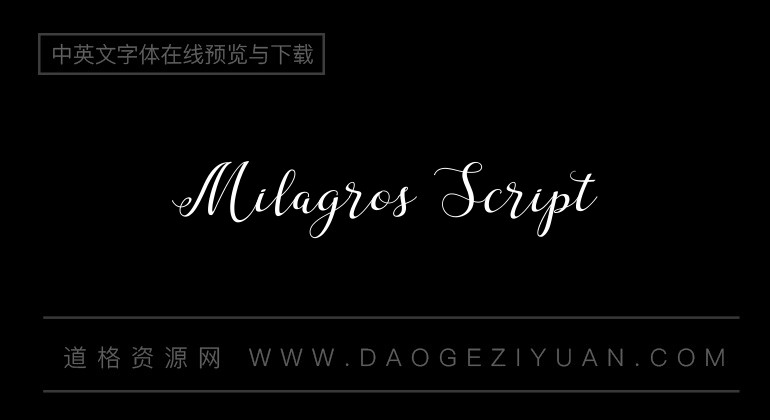
Milagros Script
Milagros Script是一种优美、流畅的手写风格字体,适用于多种设计项目,如印刷品、标志、海报、包装等。 该字体具有多种特点,如大写字母和小写字母的连字,多种替代字符、连字和装饰元素,以及多种语言支持。 Milagros Script字体的设计灵感来源于手写的书信和日记,具有独特的手写感和个性化风格。它的笔画流畅自然,让人感到愉悦和轻松。 该字体采用OpenType技术,可以在支持OpenType的软件上使用其特殊功能,如自动替换字符、上下文敏感的字形变化等。这些特点使得Milagros Script字体成为一款非常灵活和实用的字体,适用于各种设计项目。
Milagros Script是一款非常不错的手写艺术字体,具有很好的视觉感,适合于文化类的宣传设计、商业类品牌的广告和产品包装设计以及个性化文字排版等较多场景。